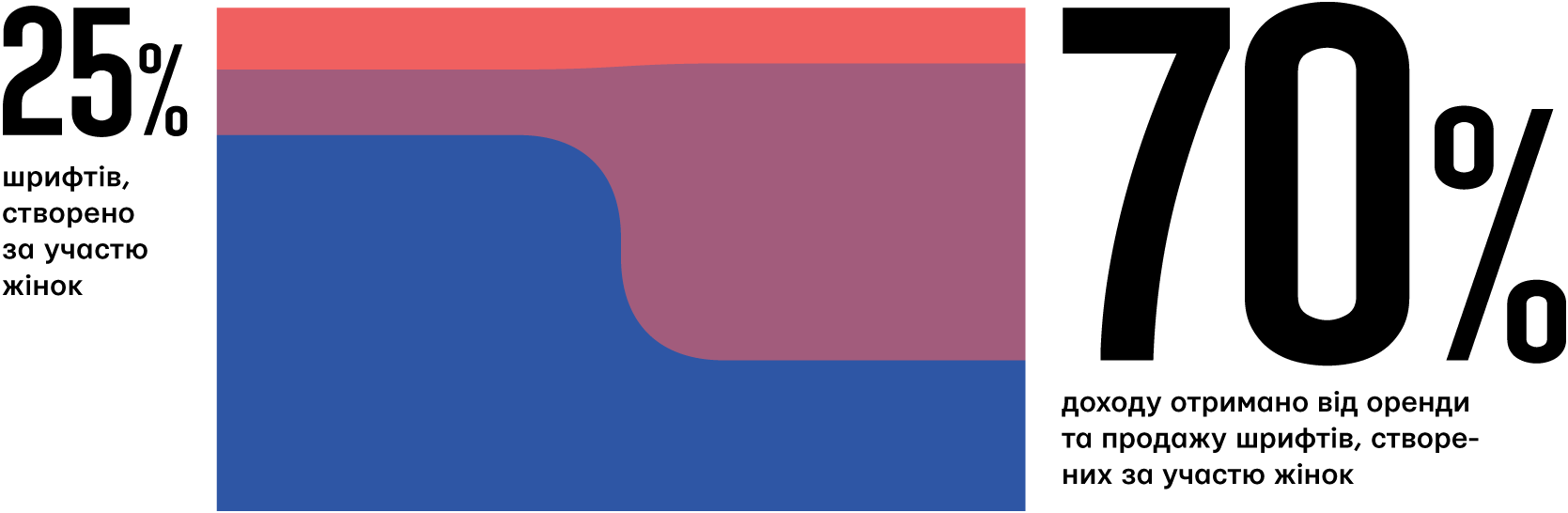
Про шрифти створені жінками
З нагоди Міжнародного Жіночого Дня ми вирішили звернути увагу на жінок в тайп дизайні та проаналізувати їх шрифти. Сподіваємося, цей аналіз стане корисним і приємним подарунком!
Раніше шрифт був переважно «чоловічою професією». Виробництво шрифтів завжди було складним творчим процесом, пов'язаним з технологіями, які вимагають спеціальної освіти та високої кваліфікації. У патріархальному суспільстві жінки майже не мали доступу до складних творчих професій. Але, на щастя, в останні десятиліття цей невиправданий гендерний перекіс поступово вирівнюється.
В Україні дизайном шрифтів на постійній основі займалися тільки чоловіки. Жінки почали входити в цю професію зовсім нещодавно, зазвичай після багатьох років роботи з каліграфією або ілюстрацією. Я сподіваюся, скоро дівчата будуть приходити також із досвідом програмування.
Сьогодні на Rentafont 126 шрифтових дизайнерів і лише 40 з них жінки:
- Світлана Акатьєва
- Арина Алафердова
- Олександра Александрова
- Анастасія Бабалян
- Гаяне Багдасарян
- Галина Баннікова
- Марина Бахирева
- Жанар Берекетова
- Вероніка Буріан
- Наталія Васильєва
- Катерина Галуян
- Олександра Єгорова
- Світлана Єрмолаєва
- Емма Захарова
- Тетяна Іваненко
- Ольга Карпушина
- Катерина Королевцева
- Олександра Королькова
- Любов Кузнєцова
- Тетяна Лискова
- Тетяна Ляшенко
- Дебора Манетті
- Людмила Михайлова
- Марина Михальська
- Марчела Можина
- Світлана Морозова
- Акіко Накашіма
- Віторія Невес
- Яна Носенко
- Ольга Панькова
- Катерина Пуленко
- Марія Селезенева
- Ельвіра Слиш
- Ірина Смирнова
- Марія Сокіл
- Ольга Умпелева
- Олена Царегородцева
- Ізабелла Чаєва
- Іраїда Чепіль
- Аніта Юргелайт
Давайте розглянемо шрифти, створені жінками на прикладі колекції шрифтів Rentafont. На сьогодні це 3921 шрифт усіх типів і призначень.
→ 988 шрифтів створених жінками — 25,2% від усієї колекції
Авторами або співавторами кожного четвертого шрифту є жінки. Які шрифти вони створюють? Чи тяжіють до певного класу чи настрою?
Популярна шрифтова класифікація
→ 486 текстових шрифтів — 49.2% шрифтів створених жінками «робочі конячки»
→ 557 шрифтів без зарубок — 56,3% шрифтів створених жінками ґротески
→ 354 шрифти з зарубками — 35,8% шрифтів створених жінками антикви
→ 63 рукописних шрифта — 6,4% шрифтів створених жінками каліграфічні
→ 14 декоративних шрифтів — 1,4% шрифтів створених жінками декоративні
Популярні асоціації та настрій
→ 738 дорослих шрифтів — 74,7% шрифтів від жінок виглядають зріло
→ 49 шрифтів для підлітків — 4,9% шрифтів створених жінками підліткові
→ 19 шрифтів для дітей — 1,9% шрифтів створених жінками дитячі
→ 798 унисекс шрифтів — 80,7% шрифтів створених жінками гендерно нейтральні
→ 150 чоловічих шрифтів — 15,2% шрифтів створених жінками маскулінні
→ 40 жіночих шрифтів — 4,0% шрифтів створених жінками фемінні
Висновки
Жінки створюють якісні й популярні шрифти широкого застосування, а не тільки милу наївну каліграфію, як могли думати деякі люди. І ці 25% шрифтів приносять 70% всього доходу Rentafont!
Ці цифри показують, що чоловіки та жінки у співпраці можуть створювати популярніші, трендові та успішні шрифти, ніж окремі автори або команди однієї статі.
Жінки також не схильні робити шрифти, пов'язані з «жіночими штучками», «жіночими журналами», «жіночими романами». Крім того, серед шрифтів, створених жінками, набагато більше «чоловічих» (15,2%), ніж «жіночих» (4,0%) шрифтів. Дитячі шрифти розподілені ще цікавіше; чоловіки роблять у 10 разів більше шрифтів для дітей, ніж жінки!
Я вважаю, що прихід жінок у професії, які раніше були зайняті переважно чоловіками, так само корисно для суспільства, як освоєння нових територій, винахід нових джерел енергії чи матеріалів.